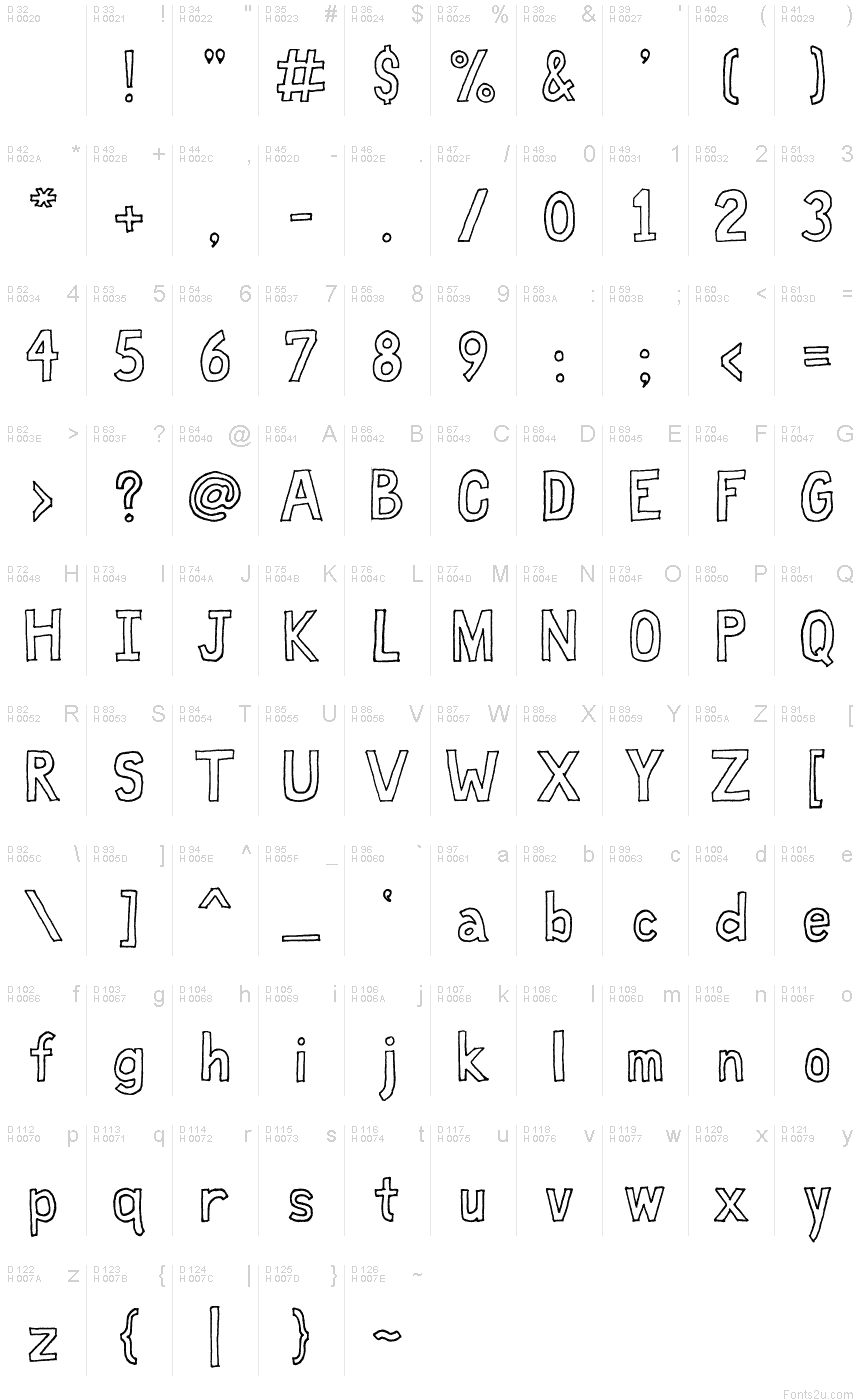
خط "Fat Free" من تصميم "Ace Fonts" هو خط عرض (display) كرتوني مجاني محدد الإطار، يتميز بالمظهر التلقائي للحروف المرسومة يدوياً بالقلم الماركر. الخطوط غير المنتظمة، ونهايات الضربات غير الحادة، والنسب المتغيرة تضفي حيوية على الحروف، بينما تمنع المساحات الداخلية المفتوحة الأشكال من أن تبدو كثيفة للغاية.
يعد الفكاهة والترفيه المخصص للأطفال مجالهما الأوضح، مما يجعله مفيداً لأغلفة القصص المصورة، ورسومات الألعاب، وعناوين كتب الأنشطة. كما يمكن أن تصبح حدوده غير المنتظمة جزءاً من الهوية البصرية لعلامة تجارية للوجبات الخفيفة أو الألعاب، لا سيما عندما يُتعامل مع الحروف وكأنها شعار توضيحي بدلاً من كونها طباعة رسمية.